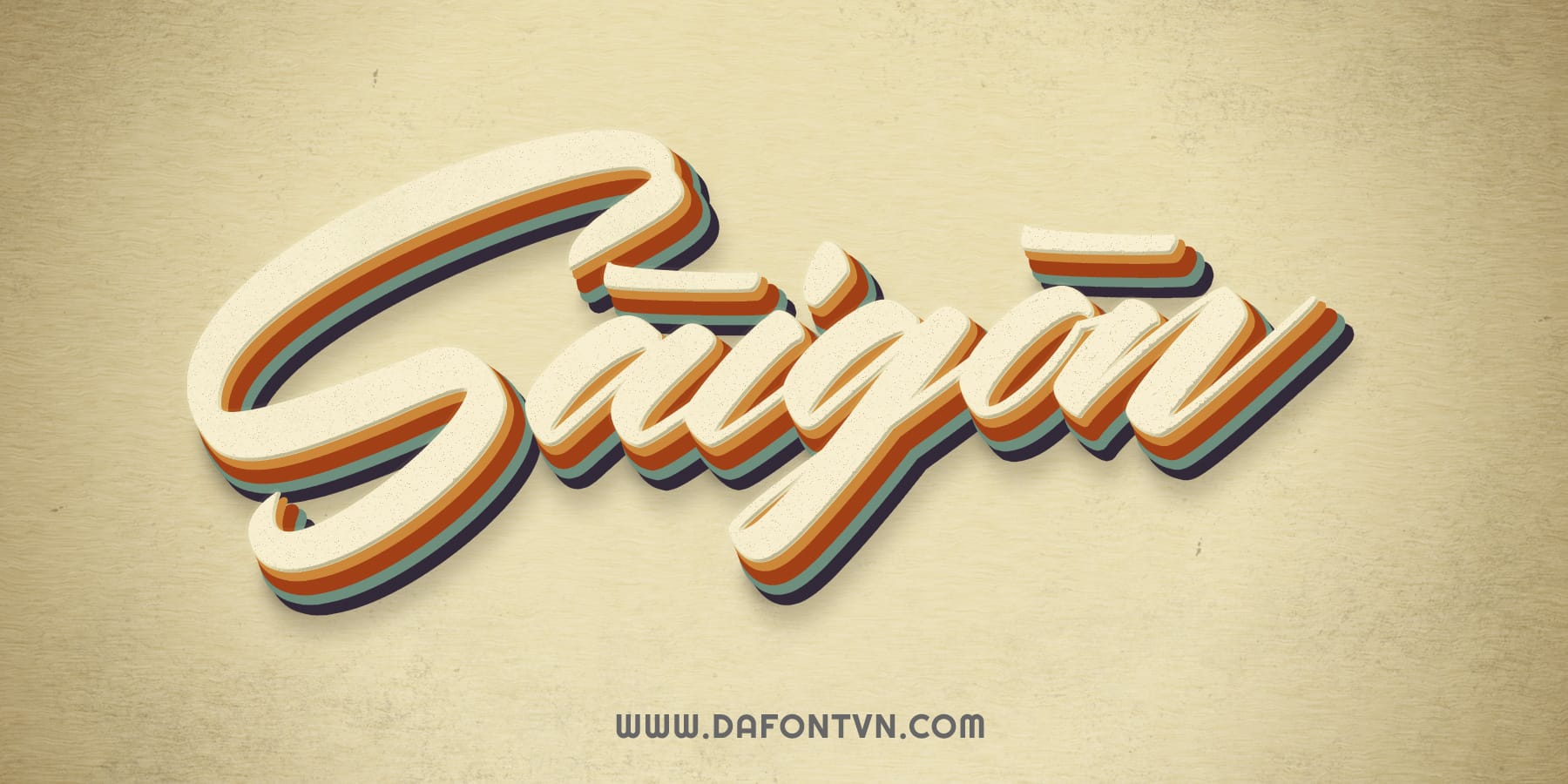
Font iCielBC Seinna Grace Việt hóa miễn phí nằm trong bộ font được Việt hóa và chia sẻ miễn phí bởi iCiel.
Font chữ này hoạt động hoàn hảo cho các các thiết kế như thiệp mời đám cưới, văn phòng phẩm, bao bì, quần áo, tờ rơi, tạp chí, tài liệu quảng cáo, tiêu đề, chữ ký, bảng hiệu, tin tức, áp phích, huy hiệu, v.v.
Font Việt Hóa Seinna Grace có 327 glyph và 82 ký tự thay thế chứa các tính năng Opentype. Seinna Grace có nhiều ký tự thay thế theo phong cách cho phép bạn làm cho mỗi từ trông hoàn toàn mới mẻ. Các dấu chấm tiêu chuẩn cũng được bao gồm để tăng khả năng sáng tạo của bạn.